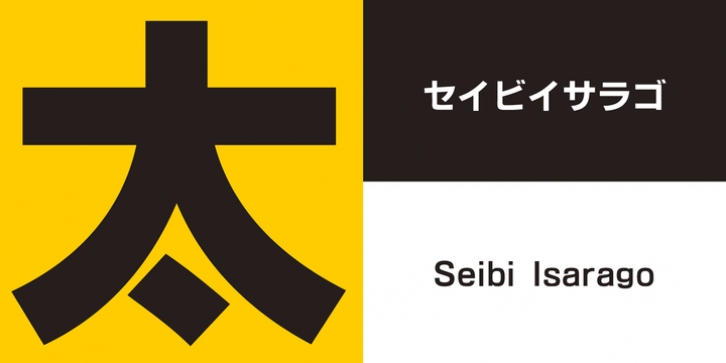
Gothic in a contemporary style designed with a broad skeleton. Considering line alignment, we have aimed for a sense of harmony in both vertical and horizontal typesetting.
フトコロ(画と画の間の空間)を広くデザインした現代的感覚のゴシック体。組み版時のライン揃えを考慮し、タテ組ヨコ組で違和感のない書体を目指しました。木版時代から手書きレタリングへと引き継がれてきた精美堂ゴシック体をデジタルフォントで再現。手書き文字を組んだ印象はそのままに、フトコロを広く現代風にアレンジしました。遠くからでも近くからでも読みやすい、目を引く見出し用ゴシックです。